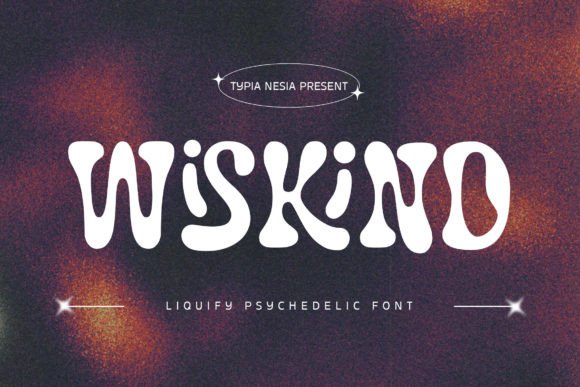
Wiskind
์˜ฌ๋ฐ”๋ฅธ ๋””์ž์ธ ์š”์†Œ๋ฅผ ์ฐพ๋Š” ๊ฒƒ์€ ์–ด๋ ค์šธ ์ˆ˜ ์žˆ์ง€๋งŒ Wiskind๋Š” ์ž‘์—…์„ ์ฆ‰์‹œ ํ–ฅ์ƒ์‹œํ‚ค๋Š” ๋›ฐ์–ด๋‚œ ์ปฌ๋ ‰์…˜์„ ์ œ๊ณตํ•ฉ๋‹ˆ๋‹ค.
POD(์ฃผ๋ฌธํ˜• ์ธ์‡„) ์ œํ’ˆ, ๊ฒฐํ˜ผ์‹ ์ดˆ๋Œ€์žฅ ๋˜๋Š” ์†Œ์…œ ๋ฏธ๋””์–ด ๊ทธ๋ž˜ํ”ฝ์„ ๋งŒ๋“ค ๋•Œ Wiskind๋Š” ์ด์ƒ์ ์ธ ์„ ํƒ์ž…๋‹ˆ๋‹ค.